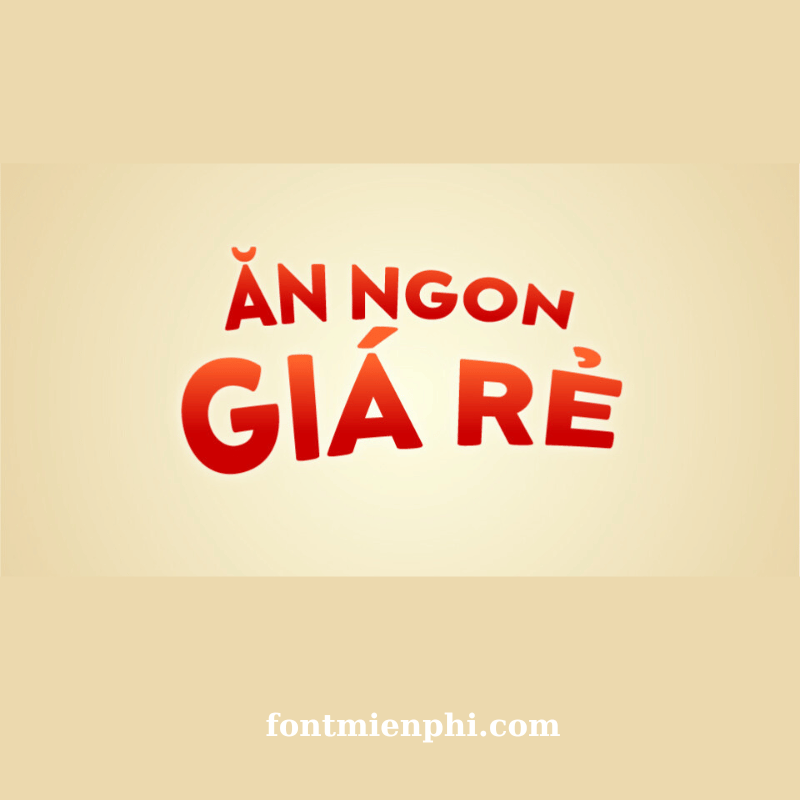
Font Việt hóa 1FTV VIP Neufreit Extra Bold
Font Việt hóa 1FTV VIP Neufreit Extra Bold  – Phong cách mạnh mẽ, độc đáo
Font Việt hóa 1FTV VIP Neufreit Extra Bold là một trong những kiểu chữ nổi bật với phong cách mạnh mẽ, đậm nét và hiện đại. Được thiết kế dành riêng cho ngôn ngữ Tiếng Việt, font chữ này phù hợp với các dự án sáng tạo, thiết kế đồ họa, logo, banner quảng cáo hay in ấn, mang lại sự chuyên nghiệp và ấn tượng.
• Kiểu chữ đậm, cá tính: Với độ dày nét vượt trội, Neufreit Extra Bold tạo điểm nhấn mạnh mẽ, phù hợp với thiết kế cần sự thu hút.
• Hỗ trợ Tiếng Việt chuẩn: Font được Việt hóa hoàn chỉnh, đảm bảo hiển thị rõ ràng mọi ký tự có dấu.
• Đa dạng ứng dụng: Dùng cho thiết kế logo, poster, bìa sách, game, phim hoạt hình và nhiều ấn phẩm truyền thông khác.
• Phù hợp với nhiều phong cách từ tối giản đến phá cách.